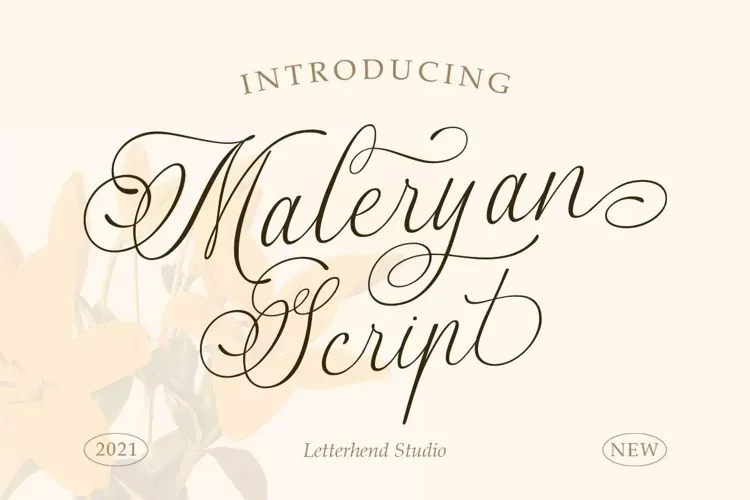
A Maleryan Font é uma elegante tipografia escrita a mão criada pela Letterhend Studio, com seus caracteres dançando sobre a linha base. Este tipo de fonte possui um fluxo natural que se torna ainda mais delicado por causa dos acordes ou “swashes”. Ideal para aplicações em cartões de convite de casamento, rótulos, logotipos, revistas e livros, a Maleryan é perfeita para os fins variados mencionados: cartões de cumprimentos e de casamento, embalagens, moda, maquiagem, papelaria, romances e rótulos. Através de sua sofisticação e delicadeza, esta fonte se destaca como a escolha perfeita para qualquer tipo de campanha publicitária.